Cominciamo dalle basi: che cos’è un font?
A dizionario l’esatta definizione di font è: un insieme completo di caratteri tipografici contraddistinti da un proprio particolare disegno e stile.
Sappiamo che possiamo generalmente classificarli in due grandi famiglie “Serif” e “Sans Serif”, tradotti dal francese “Graziati” e “Non graziati” per via del loro caratteristico disegno del carattere… ma in quanto a stili e sottostili? Beh, qui oggi abbiamo da divertirci.
I font sono spesso disponibili in diverse varianti, a partire dal peso, partendo dai classici light, regular, bold, fino ad arrivare a vere e proprie famiglie di font popolate da decine di pesi diversi e stili quali l’italic, maiuscoletto e altro ancora.
Parliamo di stili tipografici innovativi? Pensa che ultimamente molti font, detti “variabili”, offrono addirittura funzioni per poter regolare a proprio piacimento lo spessore dei caratteri, 100% personalizzabili e una capacità di reattività davvero impressionante. Particolarmente consigliati nel caso stessi cercando caratteri personalizzati per il tuo marketing!
Il mondo è pieno di font di ogni genere e tipo, la loro quantità pare pressoché infinita, eppure continuano ad esserci continue innovazioni e colpi di genio da creativi sparsi per tutto il mondo, oggi analizziamo la cosiddetta Tipografia Sperimentale.
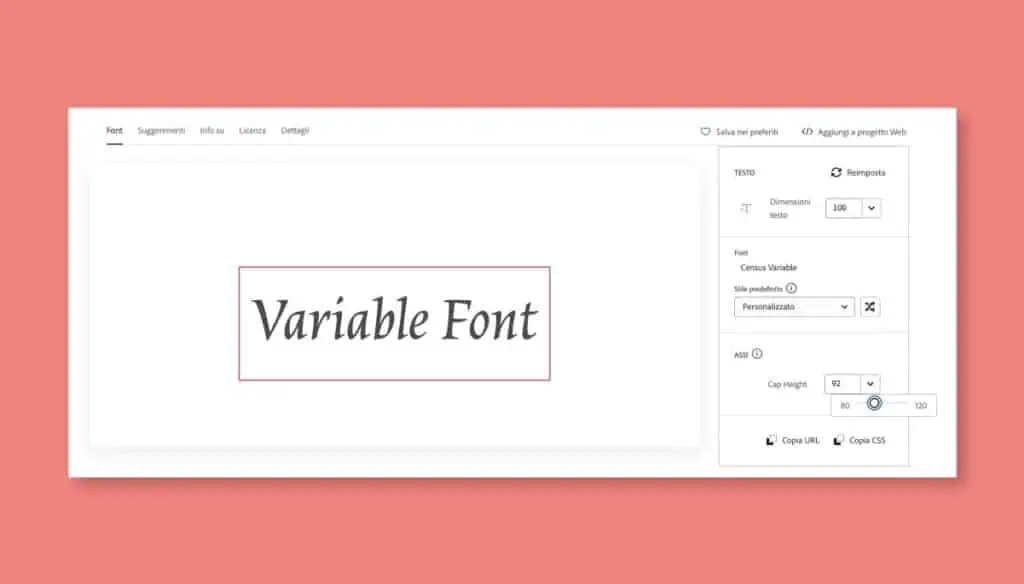
Sperimenta! Una questione di stile ed innovazione
Possiamo dire che negli anni i maestri tipografi ed i designer si sono sempre più sbizzarriti seguendo oltre che le tendenze del momento anche il continuo avanzare delle nuove esigenze ed il sempre crescente bisogno di crescita e cambiamento, andando a creare stili e forme uniche, vere e proprie potenze in quanto a personalità.
Vediamo sviluppate composizioni del tutto fuori dagli schemi, la creatività spazia ma il rigore nella costruzione rimane un caposaldo immancabile con risultati impeccabili.
Vediamo insieme alcuni esempi chiave di tipografia sperimentale:
- Font Crackly di Zuzana Licko: Ad ogni lettera è assegnato un diverso disegno di linee. La scrittura di una frase o anche semplicemente di una singola parola, crea un gioco di forme sempre nuovo, dando vita ad una serie di molteplici combinazioni e composizioni come in un pattern.
- Rotation Typography di Txaber: Font materici dove il materiale di costruzione e la superficie dell’oggetto giocano un ruolo principale. Come se si trattasse di una scultura, texture, riflessi e lucentezza divengono il punto focale, oltre a composizioni di un’efficacia disarmante.
- Tipografia cinetica di Vincenzo Marchese Ragona:
In questo caso il cavallo di battaglia è senza dubbio la tecnica di animazione che rende vivo il testo, un’applicazione di grande impatto per tutto ciò che riguarda i settori di branding e grafica del lato digital. Come dice Ragona: “Se il contenuto non cattura l’attenzione, svanisce per sempre.”
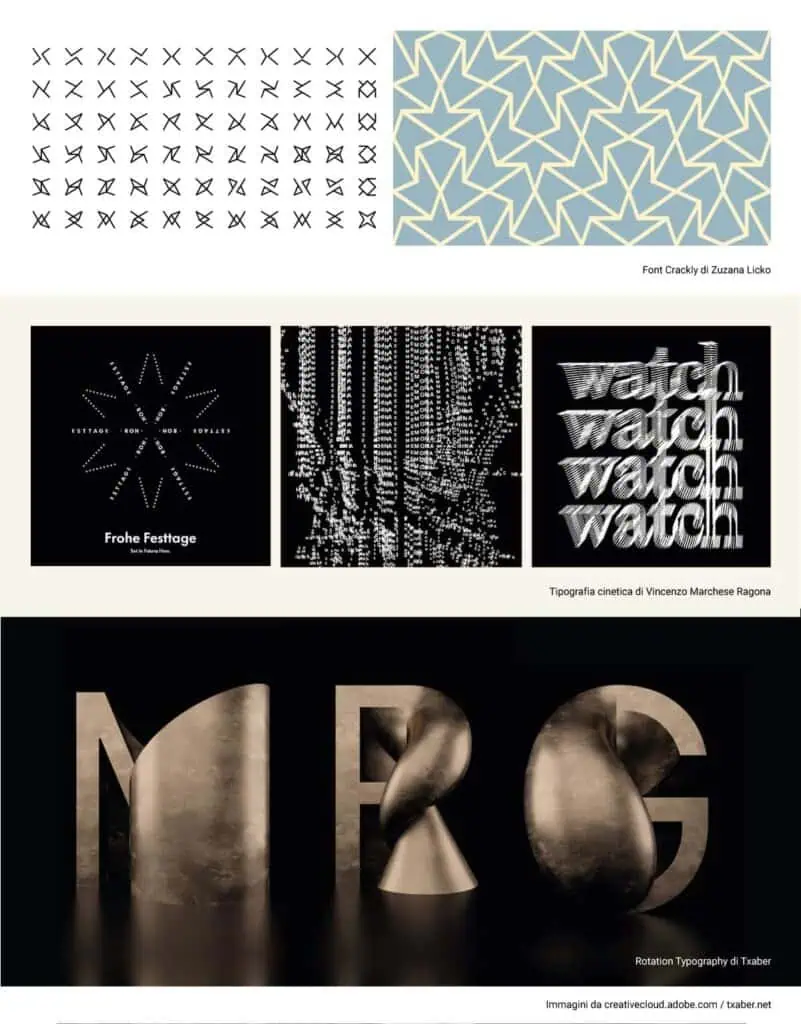
Nuovi font per il brand
L’utilizzo di font di questo tipo all’interno di un progetto di branding, ha un potenziale altissimo, incredibile in quanto ad espressione; sono caratteri talmente forti da poter diventare un’icona, rivoluzionare il tono di voce e l’immagine della società, definendo una personalità ben precisa con un tratto distintivo unico. L’utilizzo di tipografia creativa per il brand e font personalizzati per il marketing, se applicati con criterio ad un’attività o servizio, risultano estremamente impattanti ed identificativi… d’altronde ciò che abbiamo visto parla di per sé!
È importante ricordare che il branding non cura solamente il lato editoriale di stampati fisici, ma esiste un intero mondo pure nell’ambito online, con canali social e web: anche nel immenso campo del web design questi particolari caratteri stanno pian piano prendendo sempre più piede, andando a creare pagine veramente uniche e dal carattere forte e ben deciso. Pensaci, potrebbero essere uno spunto interessante!